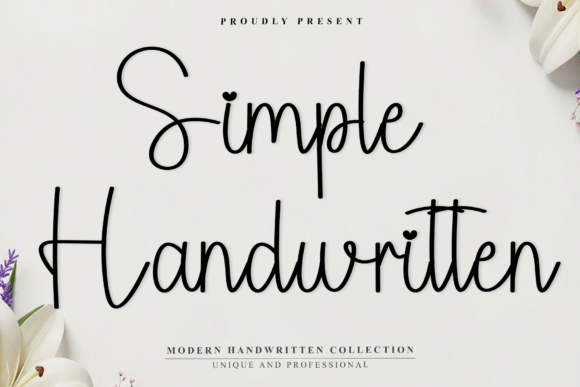
Simple Handwritten
Поиск подходящих элементов дизайна может быть сложным, но Simple Handwritten предлагает исключительную коллекцию, которая мгновенно улучшит вашу работу.
Созданный с высокой точностью, Simple Handwritten предоставляет чистые векторы, плавную типографику и коммерческую лицензию для вашего спокойствия.
Создаете ли вы продукты POD (печать по требованию), свадебные приглашения или графику для социальных сетей, Simple Handwritten станет идеальным выбором.